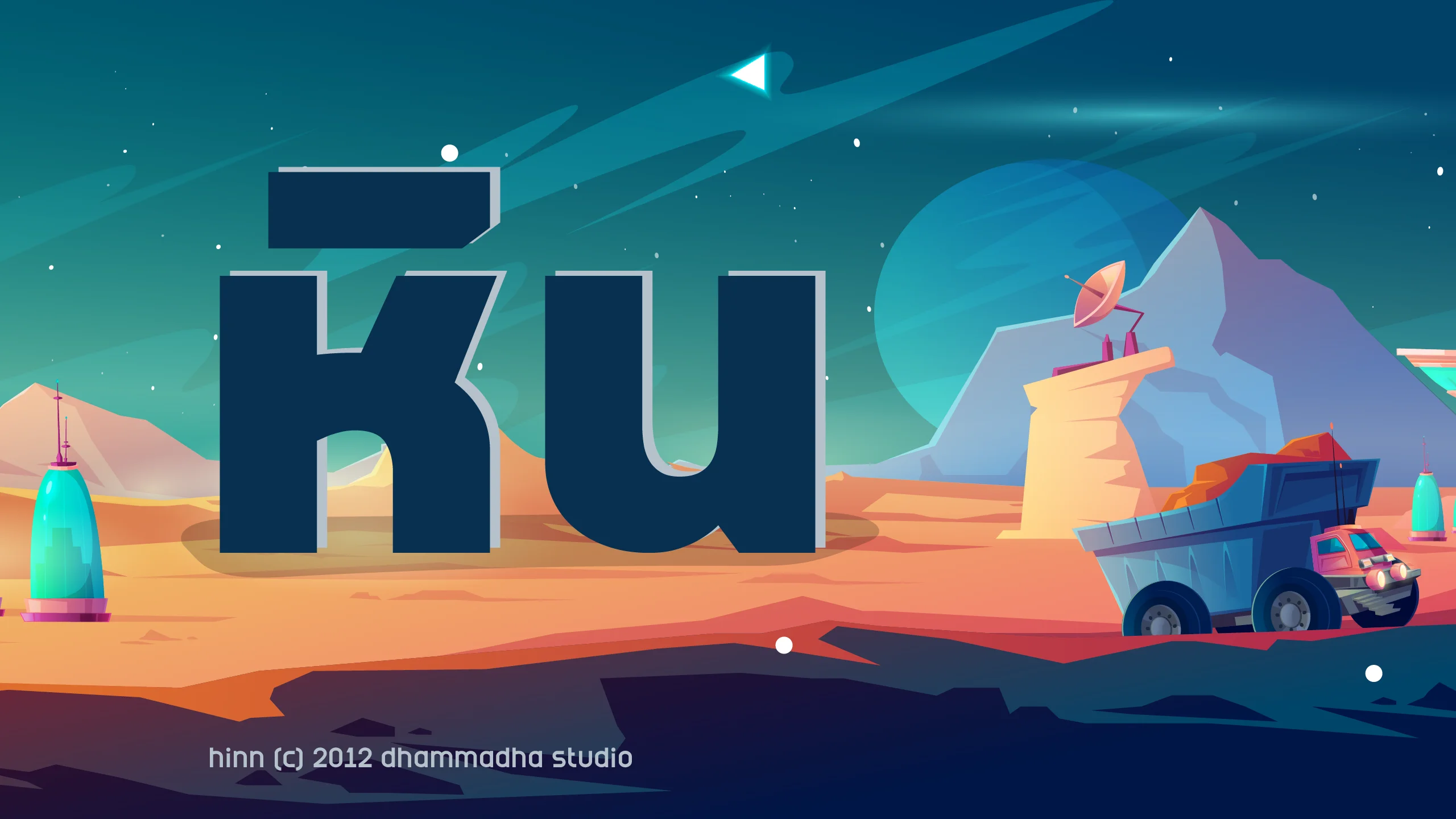
"หิน | hinn" คือฟอนต์สไตล์ Display ที่ถ่ายทอดความรู้สึกแข็งแกร่ง มั่นคง และมีพลัง ผ่านโครงสร้างตัวอักษรที่เน้นความหนักแน่นของเส้นสาย แรงบันดาลใจจากรูปทรงเรขาคณิตที่ตัดทอนจนเกิดเหลี่ยมมุมที่ชัดเจนและสมดุล สะท้อนภาพลักษณ์ของความอดทนและความยั่งยืนประดุจงานประติมากรรมหินสลัก เหมาะสำหรับงานที่ต้องการความโดดเด่นสะดุดตาและสร้างความน่าเชื่อถือให้กับแบรนด์ได้อย่างทันทีที่พบเห็น ด้วยคุณลักษณะที่ออกแบบมาเพื่อการเป็นจุดนำสายตา ฟอนต์ชุดนี้จึงตอบโจทย์อย่างยิ่งสำหรับงานพาดหัว (Headline) การออกแบบโลโก้ หรือสื่อโฆษณาที่ต้องการประกาศความชัดเจนในตัวตน แม้จะมีความหนักแน่นเป็นหลักแต่ยังคงแฝงไว้ด้วยความละเอียดลออในทุกองศา ทำให้ "หิน | hinn" สามารถยกระดับงานดีไซน์ของคุณให้ดูมีชั้นเชิง ทรงพลัง และทิ้งน้ำหนักความประทับใจไว้อย่างยาวนานในทุกชิ้นงาน